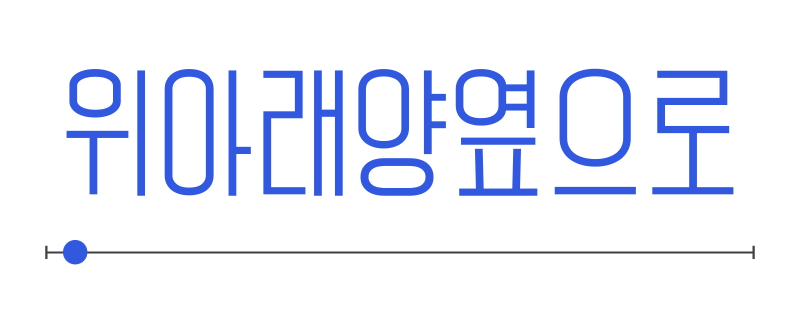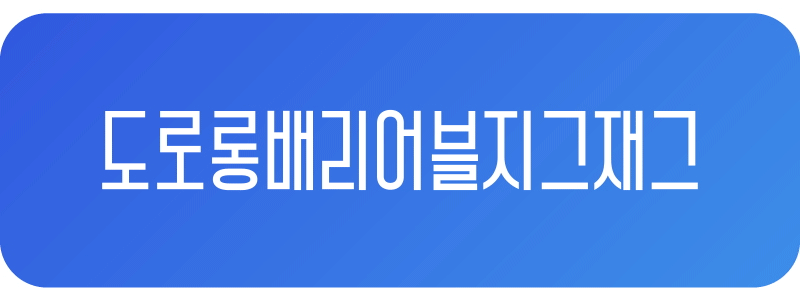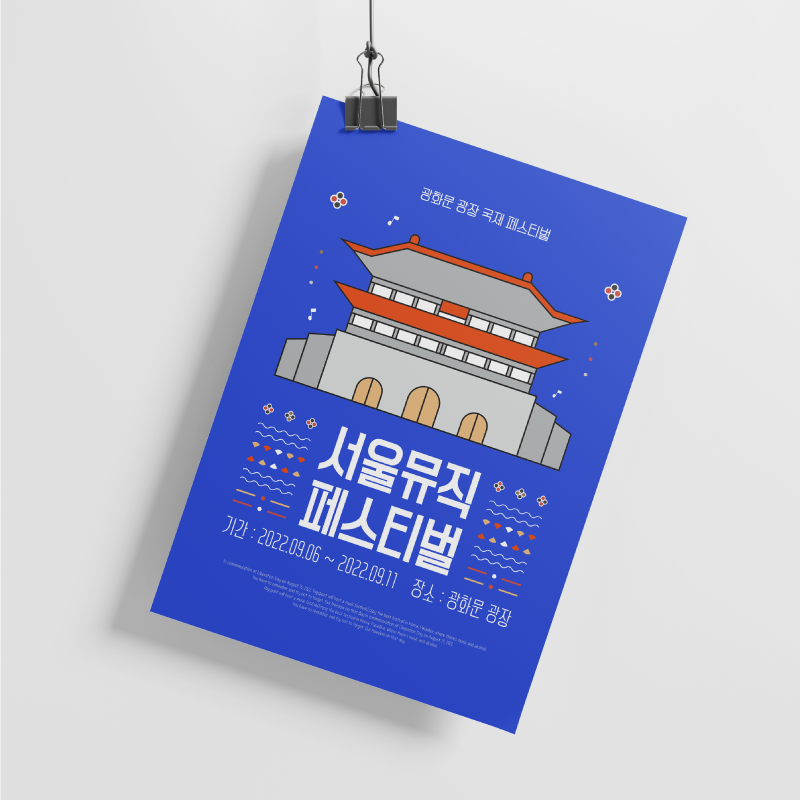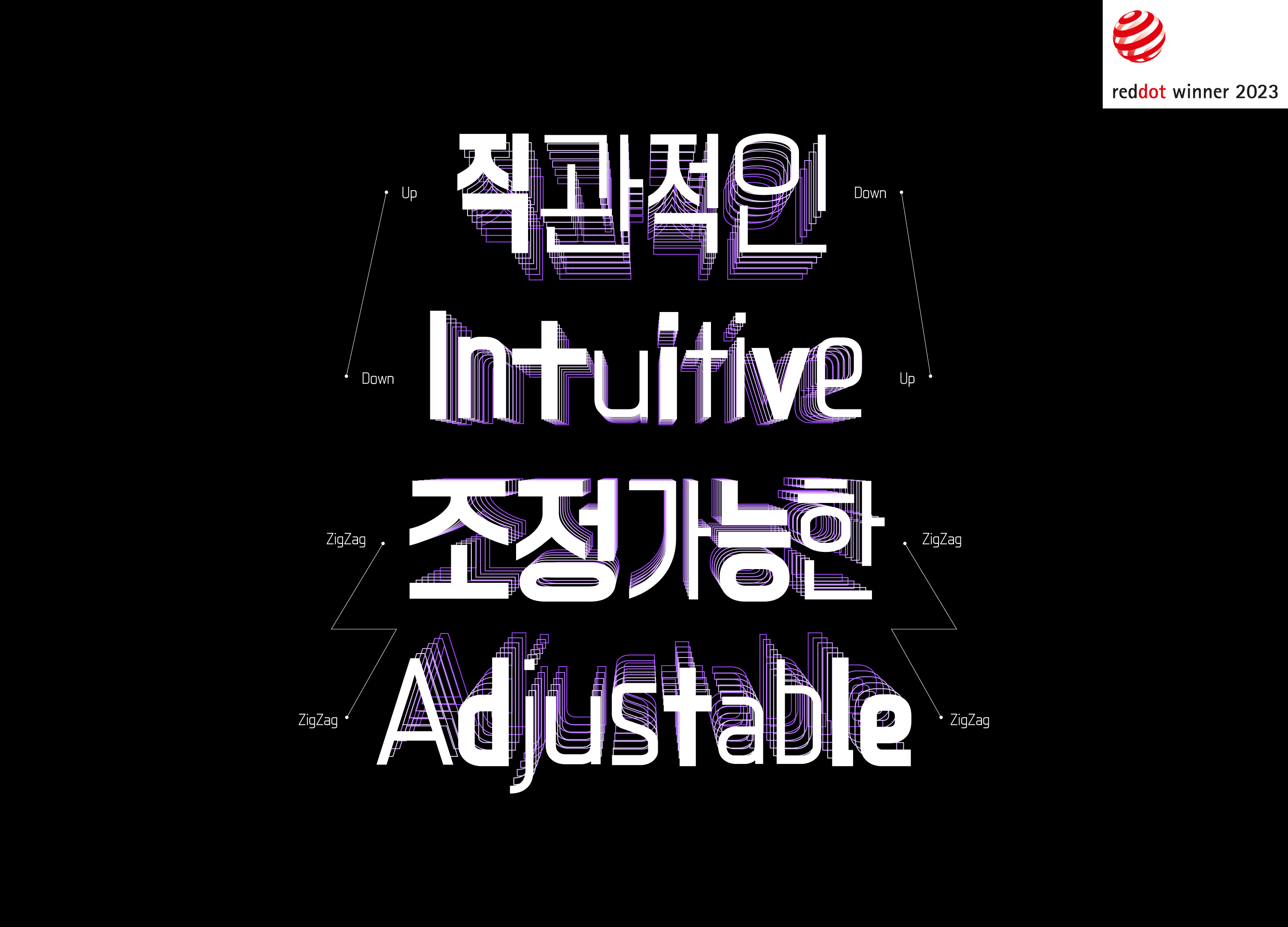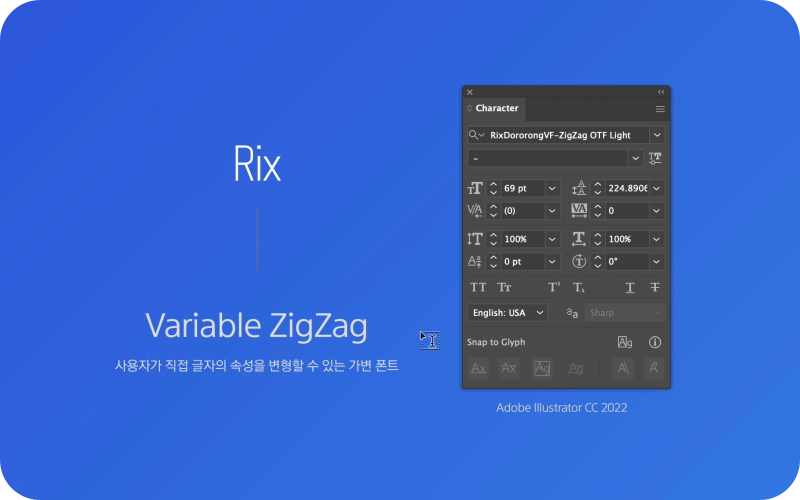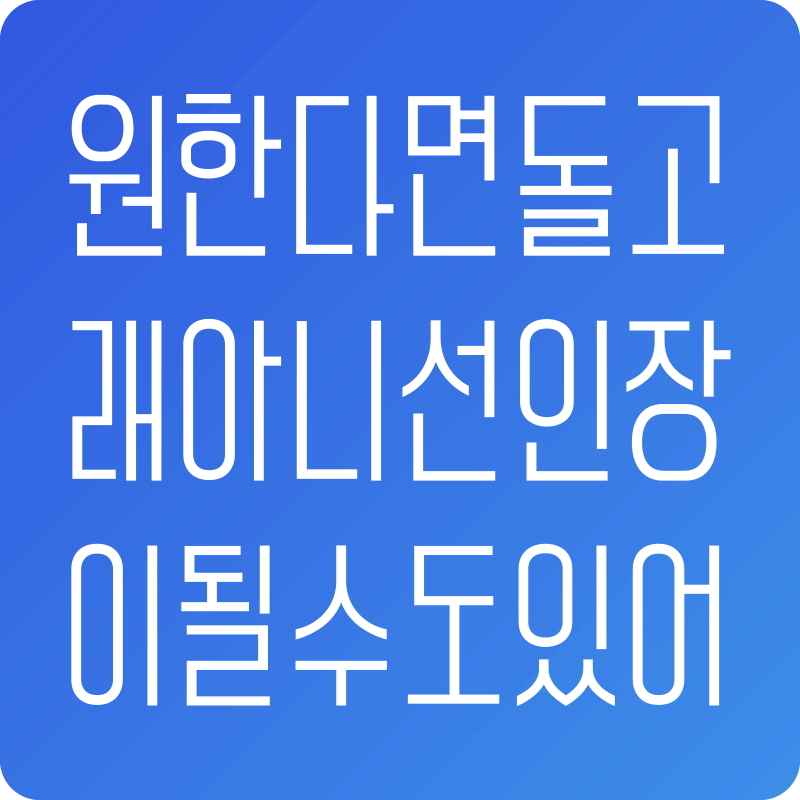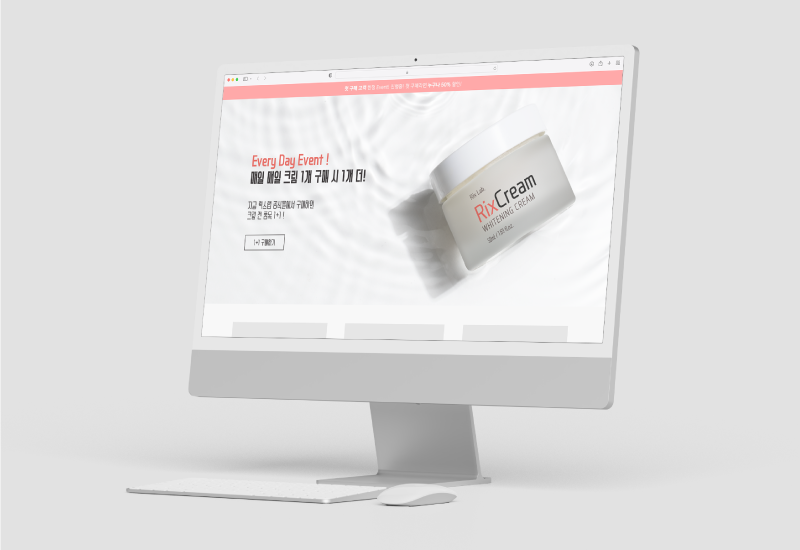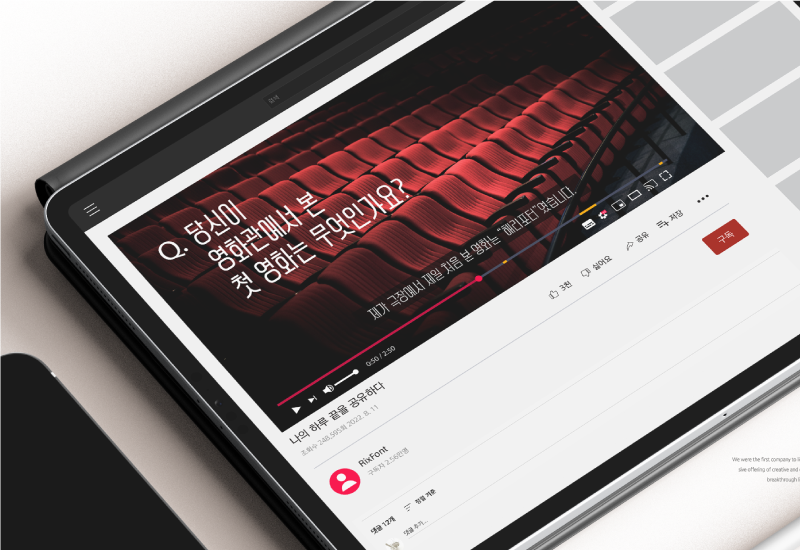
RixDororong-VF-ZigZag
Rix도로롱배리어블-UpDown 서체에서 변형을 준 배리어블 폰트입니다.
글자의 무게 중심이 앞뒤로 다르게 적용되어 더욱 재미있는 표현이 가능합니다.
굵기, 무게 중심, 너비를 혼합 전개하여 서체 패밀리의 개념을 확장합니다.
도로롱배리어블 ZigZag는 Rix도로롱배리어블-UpDown에서
무게 중심이 지그재그로 움직이는 변주를 주어 더욱 재미있는 표현이 가능합니다.
Weight를 이용해 굵기를 자유롭게 표현할 수 있습니다.
Width를 이용해 사용자가 직접 글자의 폭을 설정할 수 있습니다.